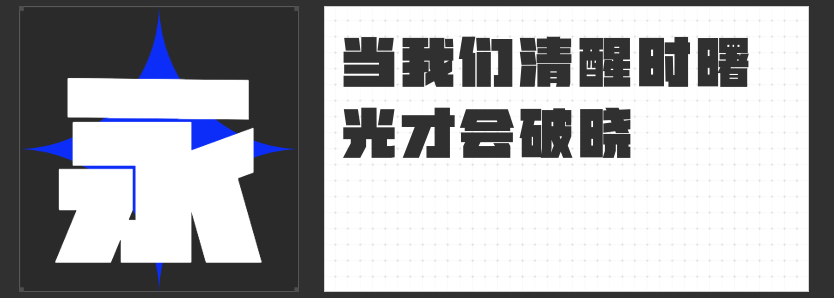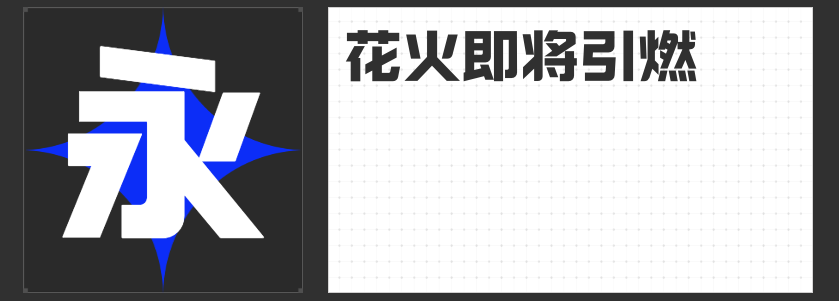
四款黑体设计利器:重塑视觉张力的专业之选
在当代视觉设计中,黑体以其简洁明快的特质成为标题、标志及导语设计的核心选择。本文精选四款非免费商用黑体,从字形结构到视觉张力进行深度解析,为设计师提供精准的字体解决方案。
一、励字勇敢黑简 特黑
这款字体以“无衬线装饰”为核心设计语言,笔划粗壮如铁铸,横竖笔画均匀分布,形成强烈的视觉冲击力。其撇捺笔画的钝化处理与横直结构的平衡,使文字在远距离阅读时仍能保持高辨识度,尤其适合科技发布会、运动品牌标志及户外广告场景。例如,在汽车品牌宣传海报中,其粗壮的笔画可强化机械力量的视觉联想。
二、励字开拓者简 特级黑
以“直线笔画”与“去钩处理”为设计亮点,这款字体通过横平竖直的几何切割,构建出棱角分明的视觉框架。中宫的适度放大与重心的精准定位,使其在屏显环境中具备出色的可读性。例如,在互联网产品的功能模块标题中,其简约的笔画可降低视觉干扰,同时通过镜像对称的撇捺设计,增强版面的科技感与秩序感。
三、励字志向黑简 特粗
通过“圆体与黑体”的跨界融合,这款字体在保留黑体刚劲骨架的同时,以拐角外圆角设计注入柔和气质。其特粗字重与高灰度填充,使文字在屏显场景中具备更强的视觉穿透力。例如,在金融类APP的界面设计中,其稳重大气的字形可传递专业信赖感,而圆角细节则弱化传统黑体的冰冷感,提升用户体验的亲和力。
四、高手兵克坚黑体
以“高灰度、少留白”为设计核心,这款字体通过极致的笔画粗细控制,形成近乎实心的视觉效果。其方正的轮廓与紧凑的字面,使其在短标题或标志设计中具备极强的视觉重量。例如,在重型机械品牌的宣传物料中,其特粗字重可强化工业力量的视觉隐喻,而灰度均匀的笔画则避免因局部过黑导致的视觉疲劳。
四款字体虽都是黑体,却能通过差异化的设计语言满足不同场景需求。设计师可根据项目调性,灵活选择或组合使用,实现视觉传达的精准表达。